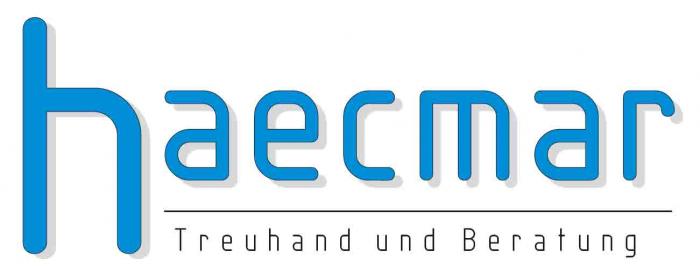
hat jemand ein Ahnung, was dies für eine Schrift ist, oder kennt eine ähnlich aussehende?
Das r ist auch nicht "original". Schönes Beispiel, dass das eine Logogestaltung und nicht nur "schnell mal aus der Schrift gesetzt" ist.
auch ganz nahe dran ist die isocpeur, die wurde IIRC mit irgendwelchen CAD-Programmen mitgeliefert und war auch IIRC vom Hersteller frei herunterzuladen. Ich google mal ... http://www.abstractfonts.com/font/13357 ... Ah ja! Autodesk war das!  Und jetzt noch mal weitersuchen ...